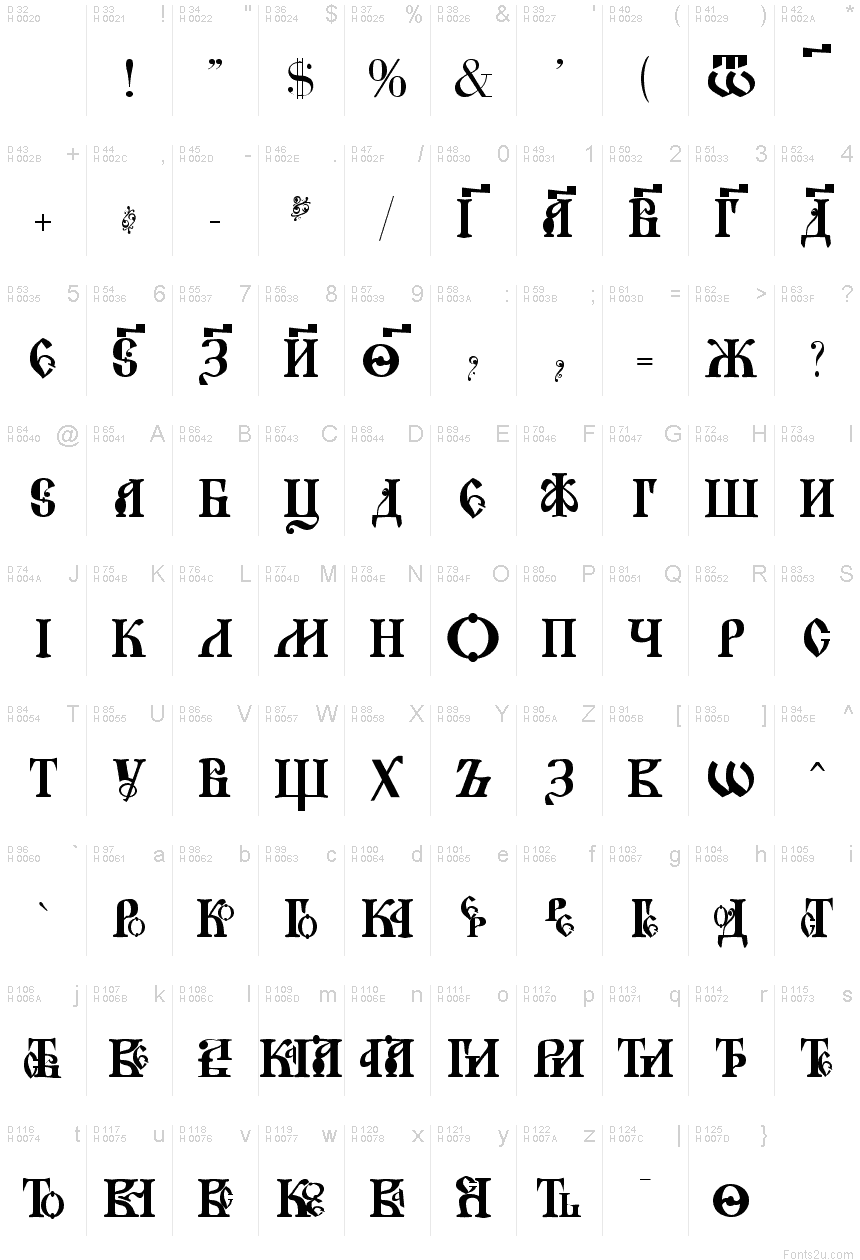
Novgorod Plain è un carattere display gratuito in stile cirillico medievale, dotato della presenza solenne e scolpita delle antiche scritture ecclesiastiche e di cronaca. Le lettere uniscono un tratto verticale importante a grazie a forma di cuneo e occasionali svolazzi interni, conferendo al carattere un aspetto monumentale e leggermente ornamentale, tutt'altro che semplicemente antico.
Si adatta perfettamente ai lavori che richiedono un tocco storico slavo: copertine di libri, poster museali, branding per festival folkloristici, titoli e aperture di capitoli sono l'ideale per questo font gratuito. Poiché la drammaticità risiede nelle forme stesse delle lettere, funziona particolarmente bene per titoli brevi, monogrammi e iniziali, dove l'eco del manoscritto lascia il segno.